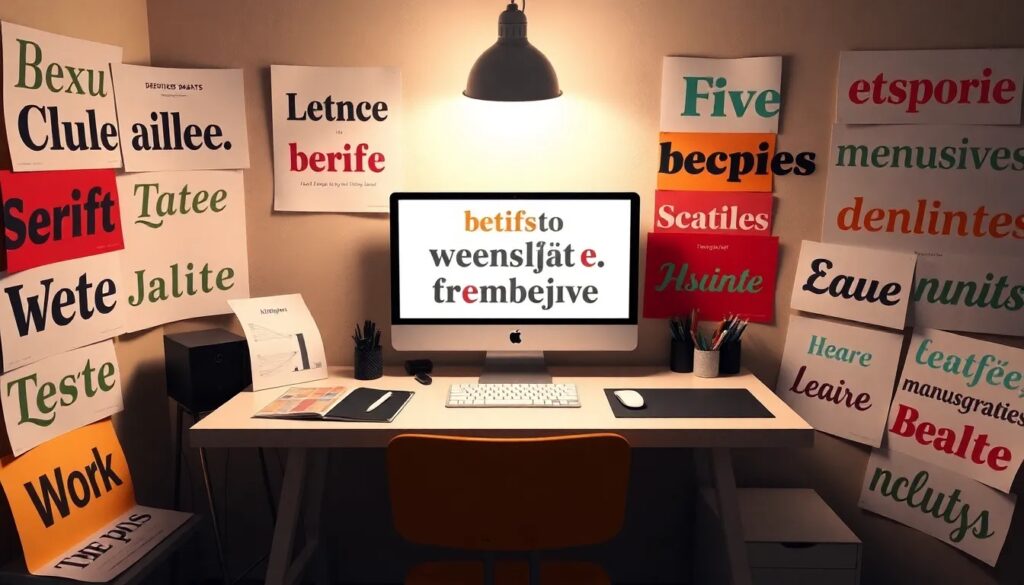
Tipografías para páginas web: las mejores opciones en 2026
La elección de tipografías para páginas web es fundamental para definir la identidad visual de un sitio. La tipografía adecuada no solo ayuda a transmitir el mensaje de manera efectiva, sino que también mejora la experiencia del usuario. En este artículo, exploraremos diversas opciones y consejos para seleccionar las mejores fuentes.
Desde la legibilidad hasta la armonía visual, cada detalle cuenta cuando se trata de tipografías para páginas web. A continuación, analizaremos qué son estas tipografías y por qué son tan relevantes en el diseño web moderno.
¿Qué son las tipografías para páginas web?
Las tipografías para páginas web son conjuntos de caracteres que se utilizan para presentar texto en entornos digitales. Estas fuentes están diseñadas específicamente para ser visualizadas en pantallas, garantizando claridad y legibilidad. A diferencia de las tipografías impresas, las fuentes web deben adaptarse a diferentes tamaños y resoluciones de pantalla.
Existen diferentes tipos de tipografías, cada una con su propio estilo y propósito. Las más comunes son:
• Serif: Tienen pequeños "pies" o líneas al final de las letras y suelen transmitir un aire de formalidad.
• Sans Serif: Carecen de esas terminaciones, lo que les confiere un aspecto más moderno y limpio.
• Script: Imitan la escritura a mano, perfectas para transmitir emociones y personalidad.
Para elegir correctamente, es esencial considerar el propósito del sitio y el público objetivo. Por ejemplo, una tienda online de moda puede optar por una tipografía elegante, mientras que un blog de tecnología puede preferir algo más minimalista.
¿Por qué es importante elegir la fuente adecuada para tu sitio web?
La correcta elección de tipografías para páginas web impacta directamente varios aspectos del diseño y la funcionalidad del sitio. Una buena tipografía mejora la legibilidad y la comprensión del contenido. Aquí algunos puntos a considerar:
• Identidad de marca: Las fuentes transmiten la esencia de la marca. Una tipografía bien elegida puede reforzar la imagen que deseas proyectar.
• Experiencia del usuario: Una buena legibilidad reduce la fatiga visual y puede mantener a los usuarios en tu sitio por más tiempo.
• Responsividad: Una tipografía adecuada se adapta a diferentes dispositivos, garantizando que el mensaje se vea correctamente en cualquier pantalla.
Al seleccionar la tipografía, considera cómo se alinea con los valores y la misión de tu marca para crear una conexión emocional con tus visitantes.
¿Cuáles son las mejores tipografías para páginas web en 2026?
Algunas tipografías se han ganado su lugar como favoritas en el ámbito del diseño web. Algunas de las mejores tipografías para páginas web en 2026 incluyen:
1. Roboto: Ideal para su uso en pantallas, es versátil y moderna.
2. Open Sans: Muy legible y amigable, perfecta para contenido extenso.
3. Montserrat: Aporta un toque contemporáneo, excelente para encabezados.
4. Lora: Una opción serif elegante, adecuada para blogs y sitios de contenido.
5. Poppins: Con su forma geométrica, es ideal para marcas que buscan modernidad.
Estas fuentes no solo son estéticamente agradables, sino que también ofrecen una gran legibilidad en diversas plataformas. Usar una combinación de ellas puede resultar en un diseño efectivo y atractivo.
¿Cómo influyen las tipografías en la experiencia del usuario?
La tipografía juega un papel crucial en la experiencia del usuario. Una elección adecuada puede hacer que el contenido sea más accesible y agradable de leer. Aspectos como el tamaño, el espaciado y el contraste son determinantes.
Un buen diseño tipográfico puede:
• Facilitar la navegación en el sitio.
• Aumentar el tiempo que los usuarios pasan en la página.
• Mejorar la comprensión del mensaje.
Por otro lado, una mala elección puede llevar a la frustración del usuario. Fuentes demasiado decorativas o difíciles de leer pueden desviar la atención del contenido principal.
¿Qué tipos de fuentes existen para diseño web?
En el diseño web, es fundamental conocer los diferentes tipos de fuentes disponibles. Estas pueden clasificarse en varias categorías:
• Fuentes web: Diseñadas específicamente para su uso en la web, generalmente se cargan desde un servidor.
• Fuentes seguras para la web: Están preinstaladas en la mayoría de los sistemas operativos y son una opción confiable.
• Fuentes personalizadas: Permiten una mayor creatividad, aunque requieren atención a la carga y rendimiento del sitio.
Las plataformas como Google Fonts y Figma son herramientas valiosas para explorar y experimentar con diferentes tipografías. Estas opciones gratuitas permiten a los diseñadores encontrar la fuente perfecta para su proyecto.
¿Cómo combinar tipografías de forma efectiva?
• Combina un tipo serif con un sans serif para crear contraste.
• Limita el uso de fuentes a dos o tres para mantener la coherencia.
• Asegúrate de que las tipografías elegidas tengan una buena legibilidad y tamaño adecuado.
Además, es importante considerar el estilo de la marca al elegir combinaciones. Por ejemplo, si deseas una imagen más formal, opta por fuentes serif; si buscas modernidad, un sans serif será más adecuado.
Finalmente, utiliza herramientas como Figma para visualizar cómo se verá la combinación en tu diseño final.